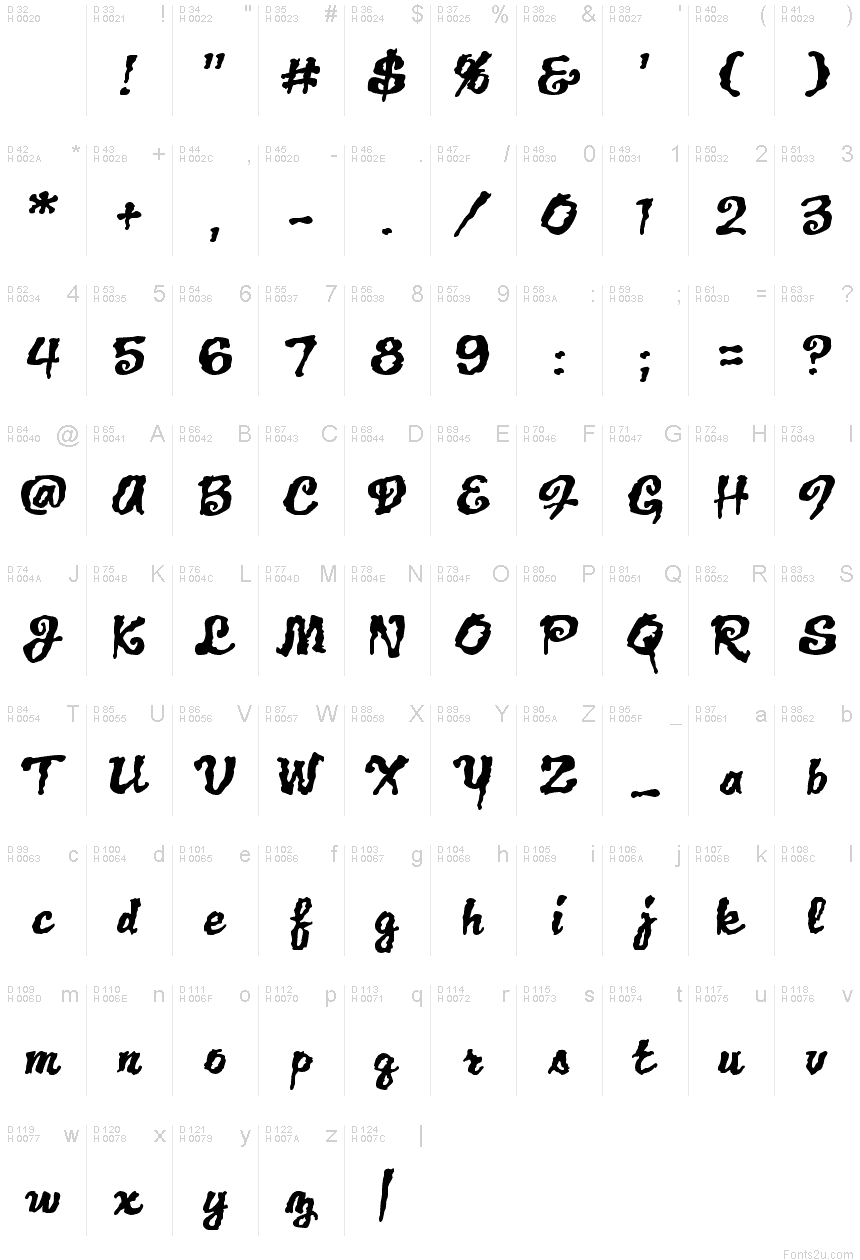
JackLantern BB od Nate’a Piekosa to darmowy krój pisma typu brush, który emanuje halloweenowym klimatem. Grube, nasycone tuszem kreski rozlewają się i zwężają niczym mokra farba na kartonie, a zaokrąglone, luźne krzywizny sprawiają, że całość jest raczej zabawna niż upiorna. Litery wyglądają jak wycięte tępym nożem – to idealne połączenie żartu i dreszczyku emocji, które w mig zamieni każdy napis w sezonowy nagłówek.
Dzięki JackLantern BB Twoje plakaty na Halloween, zaproszenia na imprezy, tytuły horrorów, szyldy do nawiedzonych domów, grafiki do mediów społecznościowych i tematyczne opakowania zyskają odpowiedni charakter. Ten darmowy font najlepiej prezentuje się w dużych rozmiarach, gdzie jego nieregularne krawędzie i specyficzny rytm mogą w pełni wybrzmieć. W przypadku tekstu głównego zestaw go z czystym, wąskim krojem bezszeryfowym, aby zachować straszny klimat, zachowując jednocześnie czytelność i równowagę projektu.
JackLantern BB